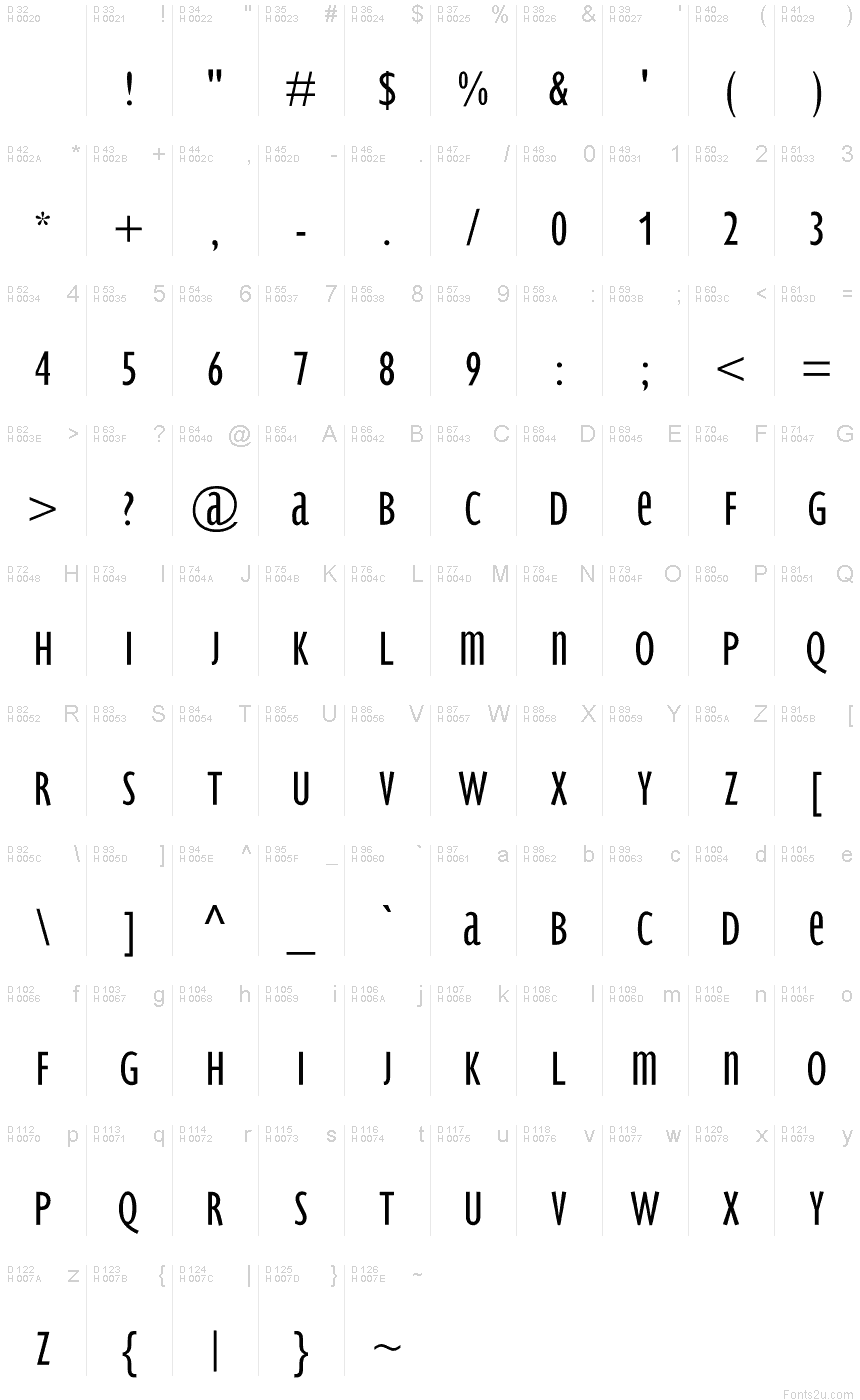
BradburySans-Light
Bradbury Sans Light to darmowy, kontrastowy krój bezszeryfowy autorstwa Manfreda Kleina, wyróżniający się wysokimi, wąskimi literami o charakterze przywodzącym na myśl początki ery cyfrowej. Cienkie kreski przeplatają się z pełniejszymi łukami, a łagodnie zaokrąglone kształty oraz jednopasmowa mała litera nadają projektowi ekscentryczny, ręcznie kreślony rytm.
Oszczędna konstrukcja sprawdzi się w plakatach literackich, okładkach niezależnych magazynów, identyfikacji wizualnej galerii, okładkach książek oraz grafikach wydarzeń kulturalnych. Jako darmowy font, sprawdza się szczególnie dobrze w krótkich nagłówkach i planszach tytułowych, gdzie nietypowe połączenie skompresowanych form, obszernych krzywych i lekko nieregularnych odstępów może w pełni wybrzmieć.